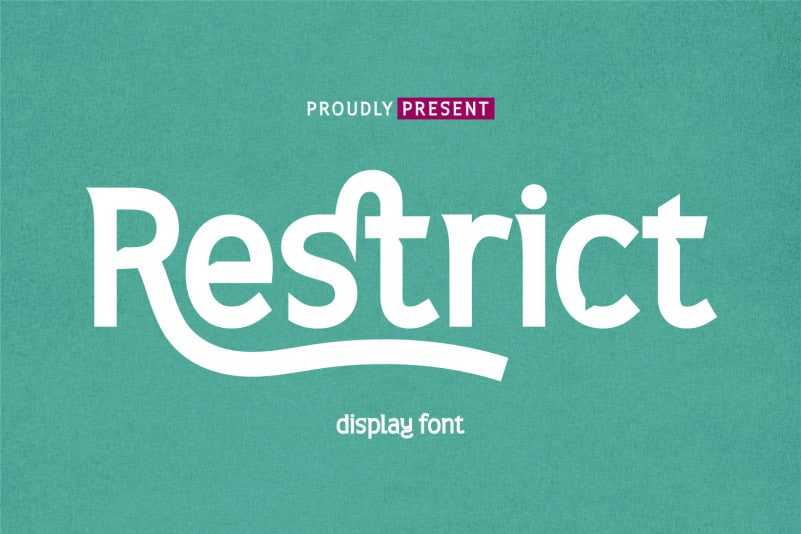
Restrict Display Font – Fonte Grátis
Restrict Display Font
A fonte ‘Restrict Display Font’ é perfeitamente adequada para uma variedade de projetos design, oferecendo tanto harmonia quanto beleza abstracta. Perfeita para aplicações como invitations de casamento, designs com frases, design de negócios no Instagram, anúncios, marcas comerciais, banners promocionais para alimentos e bebidas, texturas, cartazes, assinaturas e qualquer projeto que exija uma escrita semelhante a uma autenticidade humana. Esta fonte foi criada pelo designer twinletter e traz beleza e precisão em cada design. É perfeita para quem busca mais do que apenas uma fonte, mas deseja um impacto visual único e sofisticado que se adapta a diversos estilos de criação.